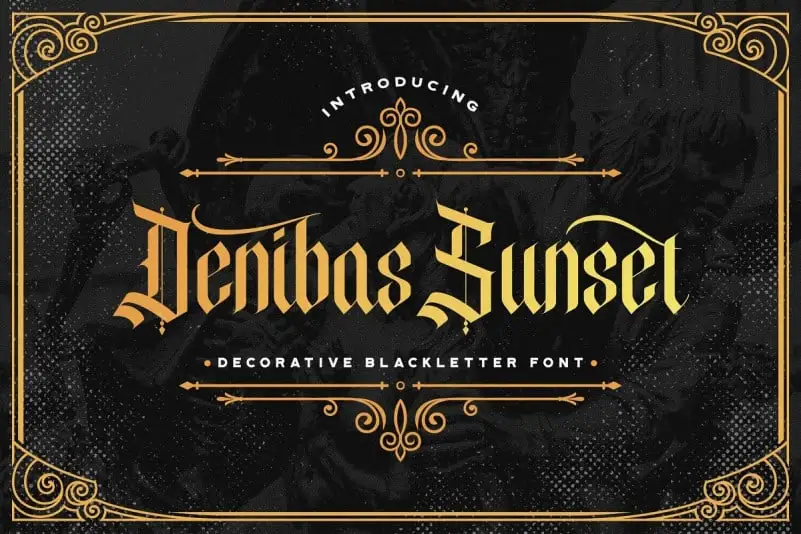
Denibas Sunset Display Font é uma fonte moderna inspirada no blackletter, com um toque vintage que certamente vai prender a atenção dos criativos e designers digitais. Combinando elegância clássica com sofisticação contemporânea, esta fonte oferece uma experiência visual única para os mais diversos projetos de design. Através dela, você pode criar identidades visuais para rótulos de produtos, selos de postes e cartazes, destacando seus títulos em headlines poderosas ou incorporá-la no branding de embalagens, badges e até mesmo selos de casamento para um toque especial. A Denibas Sunset também é uma ótima escolha para projetos vintage que requerem um ar retrô sem perder a modernidade. A fonte foi desenvolvida por StringLabs, criador da fonte, que oferece uma abrangência variada de uso e criação de identidades visuais. Perfeita para designers buscando criar ambientes digitais modernos com um toque nostálgico, Denibas Sunset Display Font é uma escolha inteligente tanto para projetos profissionais quanto para iniciantes que estão começando a explorar o mundo da tipografia.